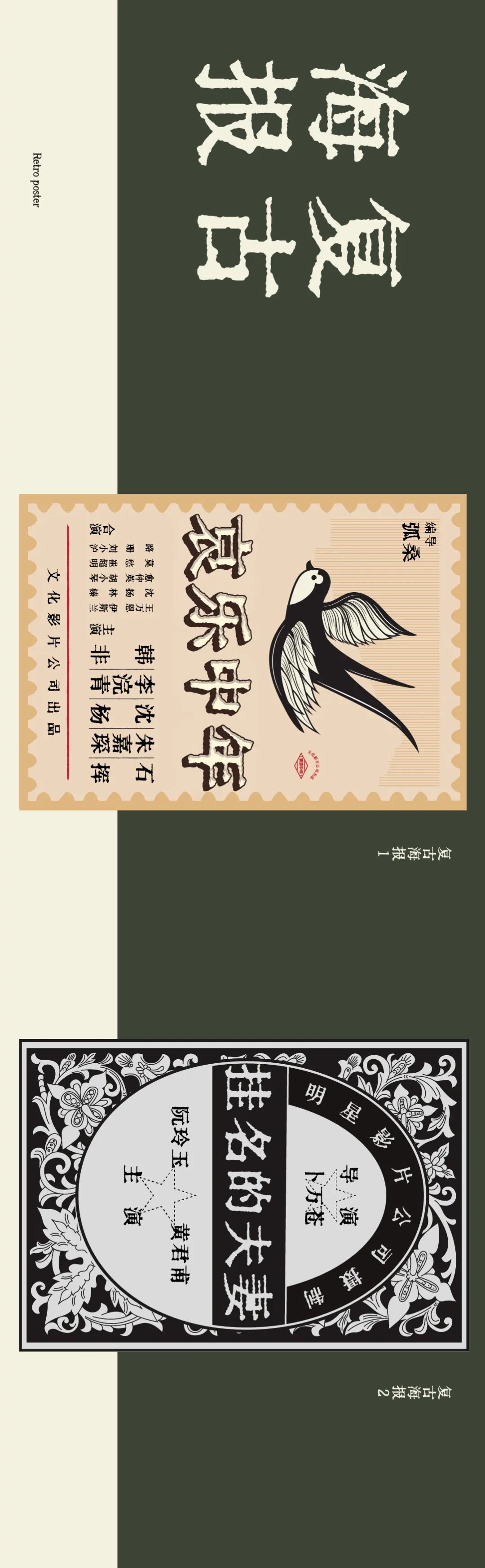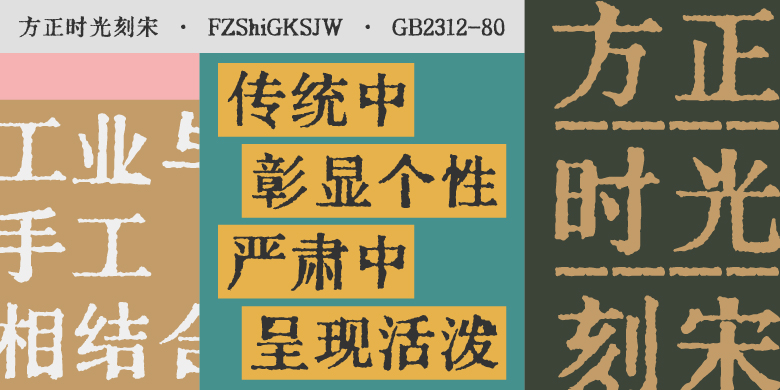
方正时光刻宋
方正时光刻宋,这款字体结构工整、笔画清晰,兼顾美观与易读性,适用于标题、正文、海报、包装、LOGO 等多种场景。字形优雅稳定,风格百搭耐看,适配日常排版与创意设计,让文字呈现更舒适、更具质感。方正时光刻宋一笔一画,皆是细节,以均衡的比例、流畅的线条打造舒适视觉体验,字形端正大气,风格简约现代。无论是商业设计、品牌宣传还是日常排版,都能轻松驾驭,让文字更有格调与力量。方正时光刻宋字体下载。
字体品牌: 方正字库 设计师:杨龙龙,田玄丹,卫欢欢 字体分类:宋体、创意字体 字体属性:精品字 字符集:大陆简体(GB2312-80)、简繁扩展(GBK) 发布时间: 2021
时光刻宋的独特洇染纹理来源于油墨过剩的印刷意外。这款字全部由人工仿画而成,却给人一种天然拓印的视觉效果。时光刻宋将工业与手工相结合,于传统中彰显个性,于严肃中呈现活泼,于怀旧中显现时尚。适用于电影海报、品牌名称、商号招牌、各类商业海报、媒体标题等。
杨龙龙、卫欢欢、田玄丹